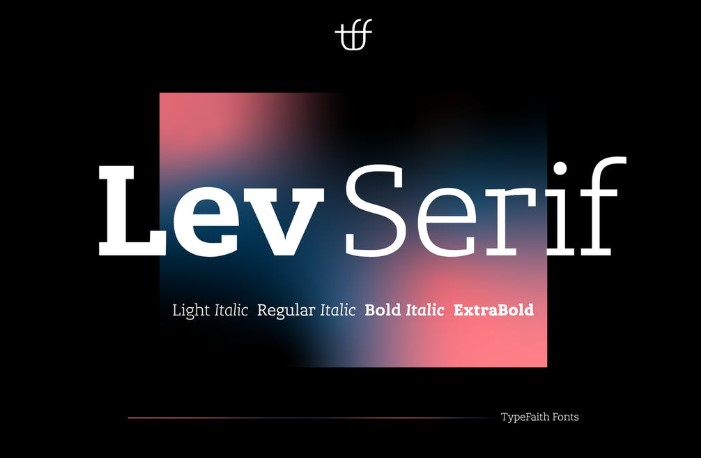
Elements.Envato Lev Serif Font
[Elements.Envato] Lev Serif Font
Лев - это плитка шрифта Serif, с прямоугольными засечками с прямыми плечами и изогнутыми связями, контрастирующими с кривыми и петлями.
Для Льва Серифа характерны толстые, блочные засечки.
Лев разработан Леоном Халстом.